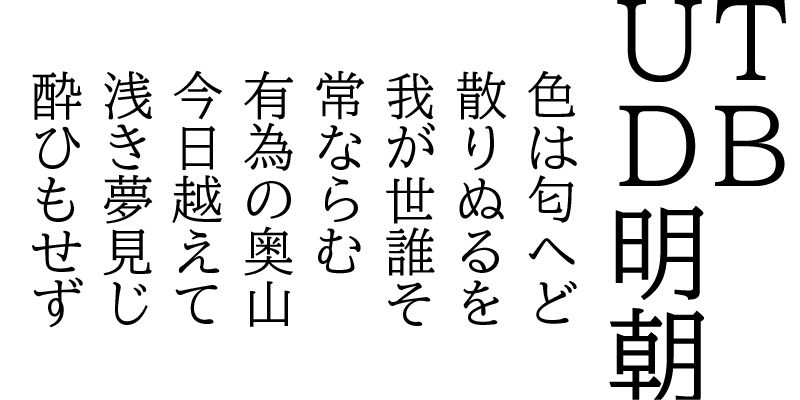
TypeBank UD Mincho 是一种通用设计的衬线字体,具有更高的易读性和可读性,同时继承了仪态高贵的 Mincho 字体的传统。由于大多数 Mincho 字体的水平笔划很细,因此某些显示和标志难以阅读,特别是对于有视力问题的人来说更是如此。TypeBank UD Mincho 的设计基于 TypeBank Yokofuto Mincho,其水平线条比传统的 Mincho 字体更粗。对于通用设计版本,dakuten (゛) 和 handakuten (゜) 发声标记设计得更易读,字形经过调整以保持平衡,同时具有更大的字体和更宽的开口。